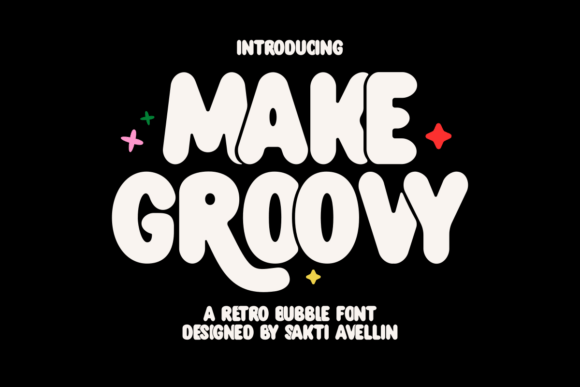
Make Groovy
Make Groovy – A Fonte Bubble que Revive o Espírito dos Anos 70
Se você procura uma tipografia que combine vibração retro com versatilidade moderna, Make Groovy é a escolha certa. Essa fonte bubble, inspirada nas cores e no ritmo da década de 70, traz um toque chic, descontraído e cheio de personalidade para qualquer projeto.
Por que Make Groovy se destaca?
- Design ousado e ondulado – Traços arredondados e fluídos que criam um visual amistoso e ao mesmo tempo impactante.
- Caracteres alternativos exclusivos – Como o rabo prolongado da letra “R”, que permite variações criativas em logos e tipografias personalizadas.
- Alta legibilidade em tamanhos grandes, ideal para screen printing em camisetas oversized, moletons, bonés e tote bags.
- Aplicação multifacetada – Perfeita para rótulos de snacks, bebidas artesanais, produtos de skincare teen, cafés, lojas de bolos e marcas de moda infantil ou adolescente.
Onde usar Make Groovy?
Make Groovy brilha em contextos que pedem um toque nostálgico, porém fresco:
- Identidade visual de cafeterias e lojas de bolos que desejam transmitir calor e criatividade.
- Branding de marcas de moda teen – camisetas, hoodies e acessórios que precisam se destacar nas redes sociais.
- Rótulos de bebidas artesanais e snacks que buscam atrair o público jovem e descolado.
- Materiais de marketing – flyers, banners e posts digitais com um visual retro‑moderno.
- Projetos DIY – chaveiros, canecas, quadros e outros itens personalizados para venda ou presente.
Conclusão – A escolha certeira para quem quer ser groovy
Com sua energia vibrante dos anos 70 e flexibilidade de uso, Make Groovy transforma qualquer design em um ponto de destaque visual. Seja para impressão em tecidos, etiquetas de produtos ou criações artesanais, esta fonte entrega charme, originalidade e impacto de forma irresistível. Não perca a chance de dar vida à sua marca com a dose certa de nostalgia e modernidade – escolha Make Groovy e deixe seu projeto brilhar!